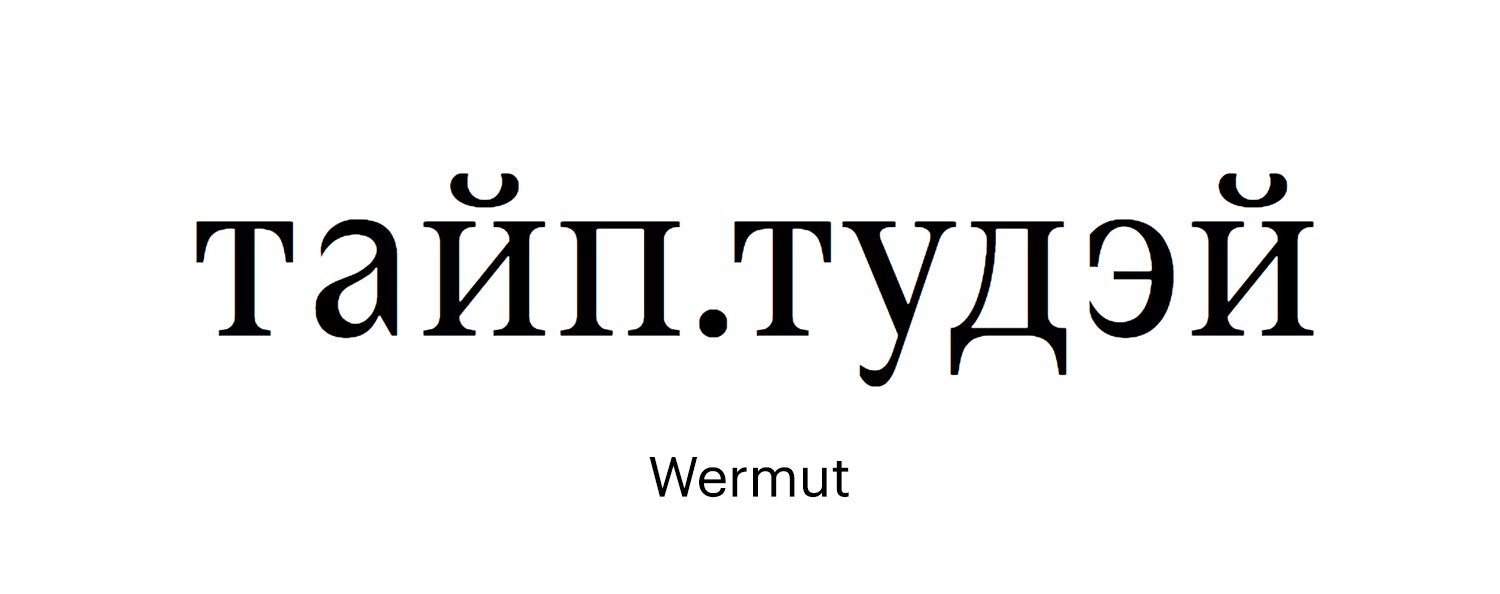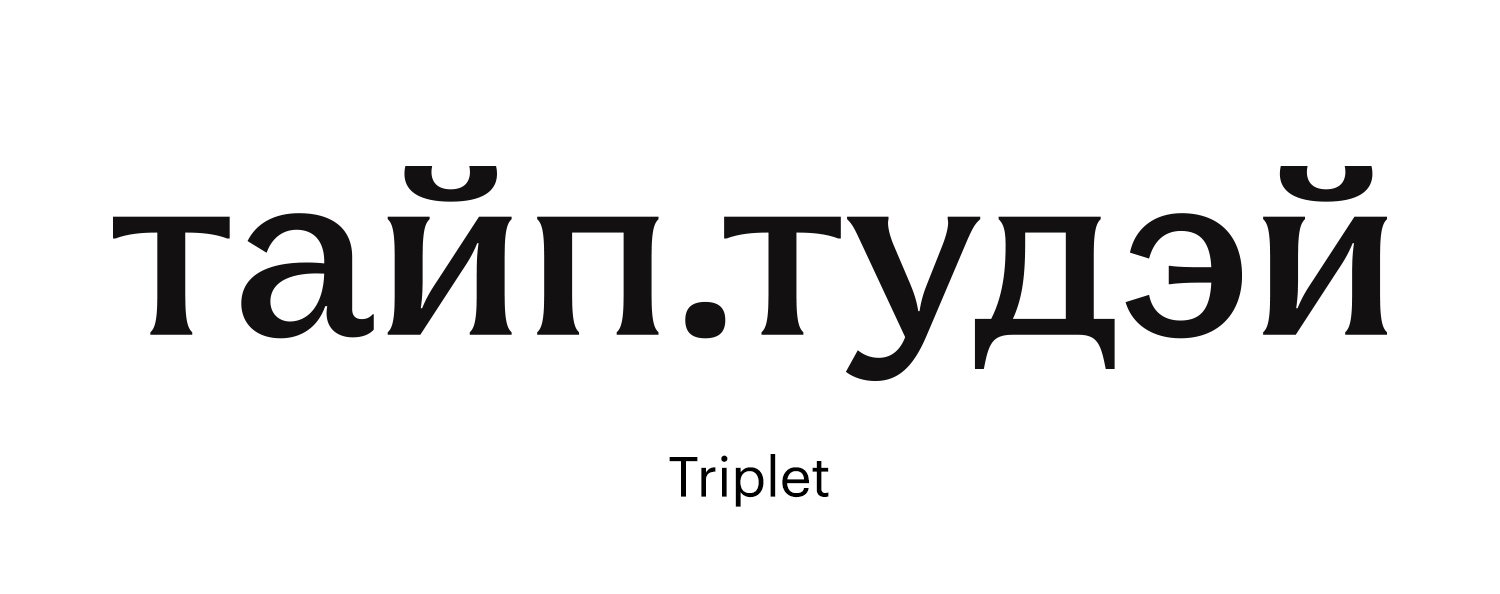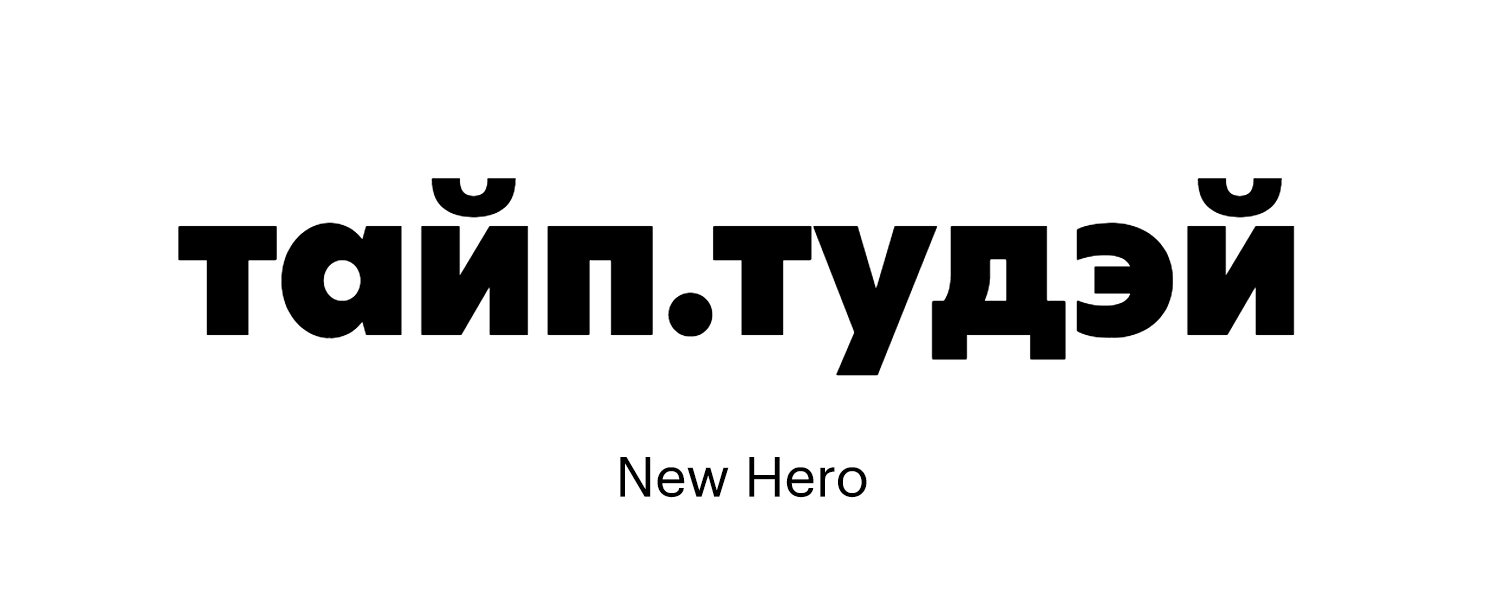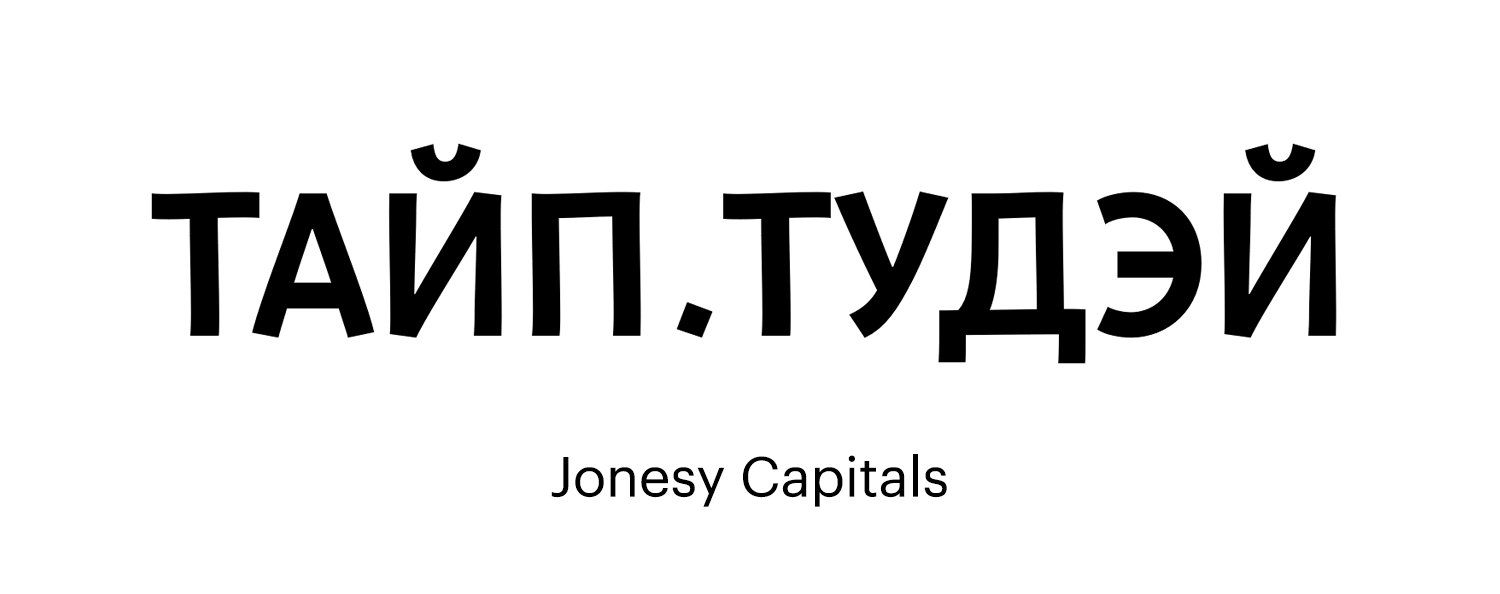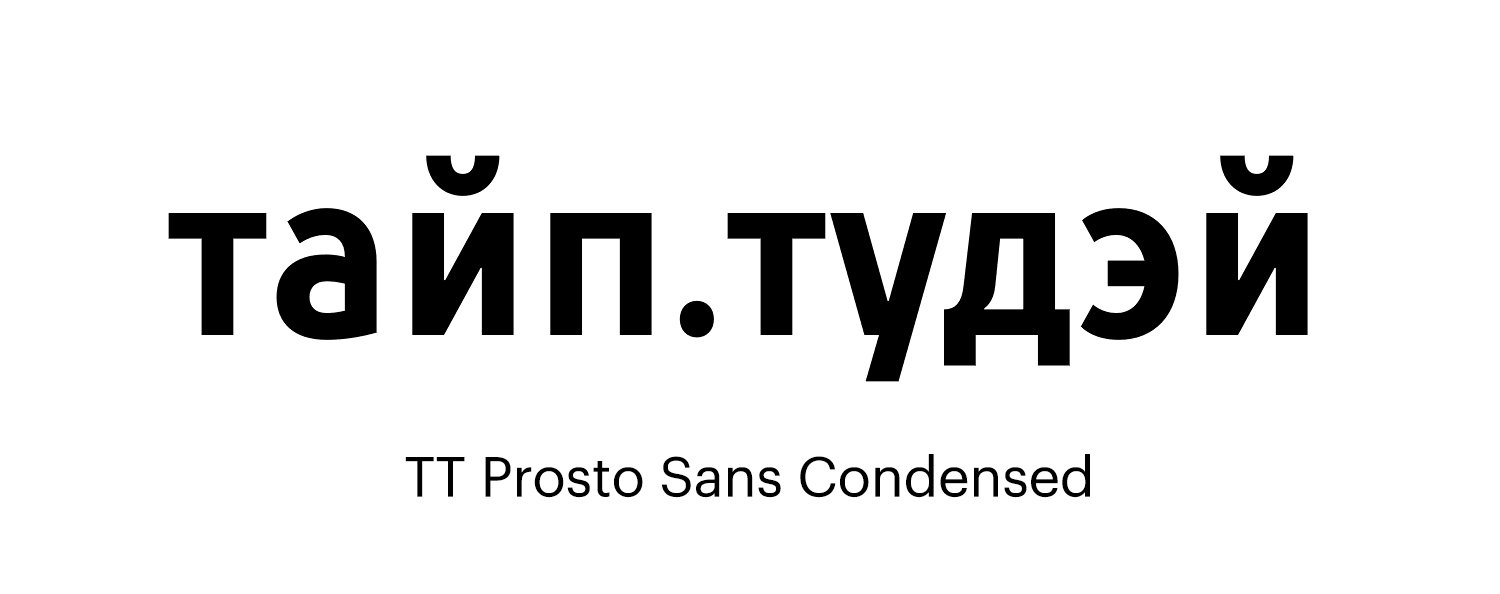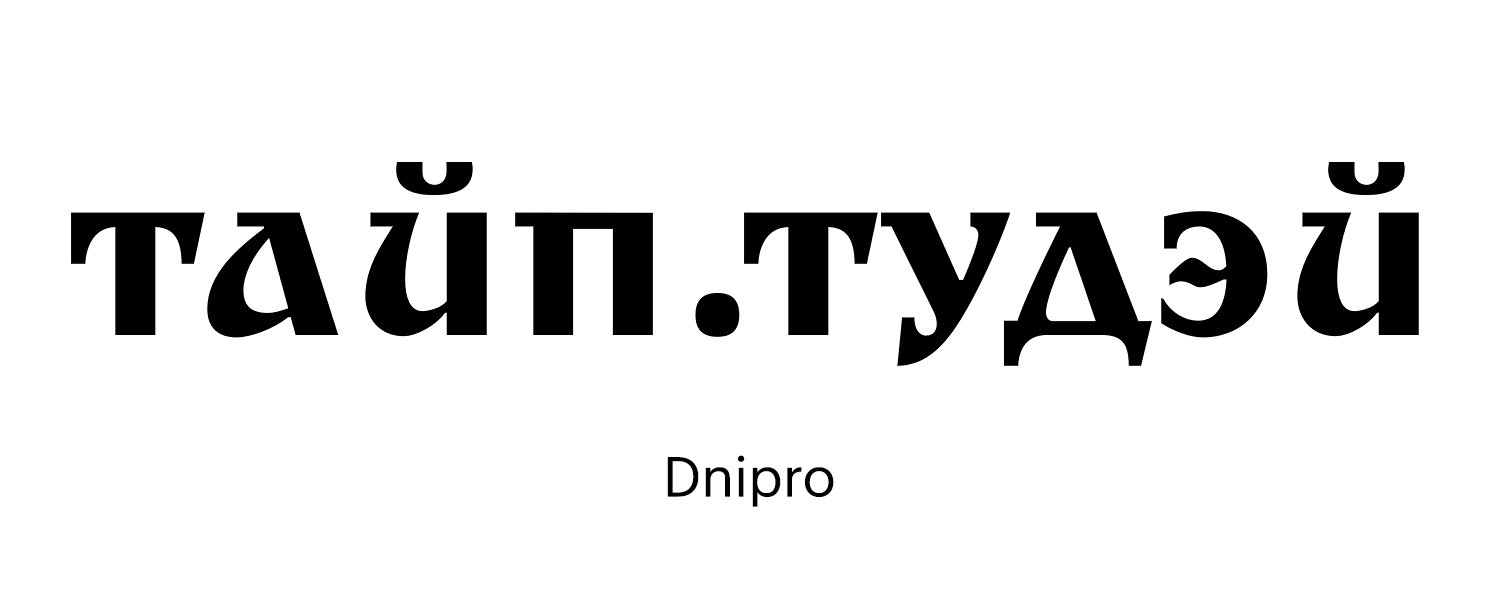
С каждым годом на рынок выходит всё больше новых шрифтов. Уверенно растёт и кириллический рынок. Совместно с коллегами из журнала «Шрифт» мы составили наиболее полный список новых шрифтов с кириллицей. А потом разложили их по полочкам, пользуясь исключительно своими собственными субъективными предпочтениями и представлениями о прекрасном.
Наши любимые шрифты
Шрифты 2016-го года, заинтересовавшие нас больше всего.
Euclid Flex
Suisse Int’l
Wermut
Качественные универсальные шрифты
Проекты 2016 года, качество кириллицы в которых мы субъективно считаем высоким, а спектр применения — широким.
Alergia Grotesk
Alergia Remix
Alethia Pro
Baskerville Display PT
Diodrum
Flai
Mediator
New Hero
November
October
Triplet
Scientia
STIX Two Text
Шрифты точечного использования
Проекты, в которых мы отмечаем прежде всего яркость графической идеи. Во многих случаях это шрифты не для широкого спектра задач, а для разового, точечного использования.
Amphibia
Appetite Pro
Barberry
Bickham Script Pro 3
Bombarda
Cadmus Pro
Mandelshtam
Dnipro
Eurostile Next
GT Eesti
Kyiv
Manicotti
Manu
Skolar Sans Pan European
Strelka Ultra
Tavolga
Остальные
Asterisk Sans Pro
Agio
Adamant Sans
Barbecue
Bw Surco
TT Blushes
Brummell
TT Bricks
Bergen Sans
TT Bells
Chocolates Condensed
Centrale Sans Pro
Citadina
Clone Rounded
TT Coats
Corals
TT Cottons
Deleplace
Dempster
Diaria Sans Pro
Din Serif
Economica Pro
Fabrizio
Fada
Furius
FF Signa Slab Stencil
Gilroy
Gill Sans Nova
Joanna Nova
Joanna Sans Nova
Jonesy Capitals
TT Lakes
Lisboa & Lisboa Sans
TT Lovelies Script
Kongo Pro
Midpoint Pro
TT Moons
Misty
Mrs Berry
Mr Dum Dum
Nitti
Noir
Noto Sans
Noto Serif
TT Octas
Pleinair
PF Centro Slab Press
TT Pines
Posterama
TT Prosto Sans Condensed
Qanelas Soft](http://www.myfonts.com/fonts/radomir-tinkov/qanelas-soft/)
Quinoa
[Quiza Pro](https://www.myfonts.com/fonts/catharsis-fonts/quinoa/)
TT Rabbits
Rogan
Rosengarten
Sibra
TT Squares Condensed
TT Supermolot Condensed
Sybilla Pro
TT Teds
TT Walls
La Mona Pro
Pintanina Pro
Lolapeluza
Шрифты 2016 года из коллекции type.today
В нашей коллекции есть шрифты, в которых кириллица появилась именно в 2016 году.
Kazimir Text
BigCity Grotesque Pro
First Prize
Giorgio Sans Cyrillic
NWT Bodoni